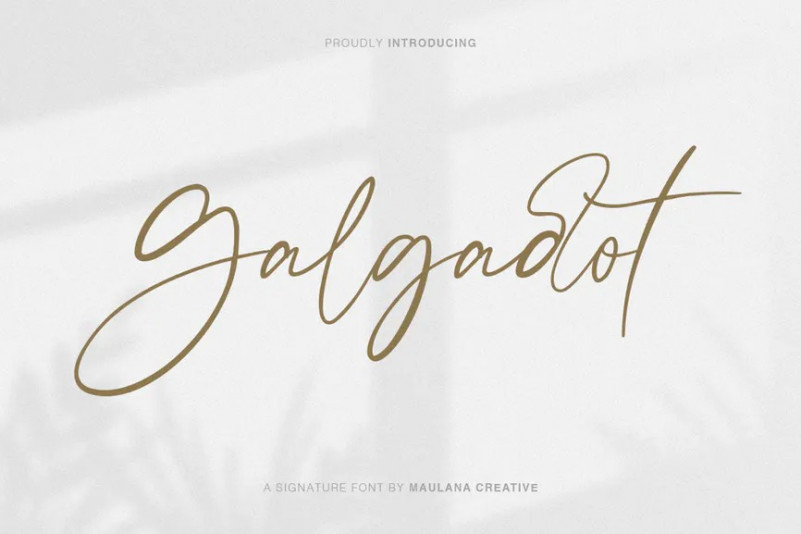
Galgadot Font
Donnez à vos créations une sensation artisanale authentique. « Galgadot » convient parfaitement à la signature, à la papeterie, au Logo, aux citations typographiques, à la couverture de magazines ou de livres, à l’en-tête de site Web, aux vêtements, à l’image de marque, à la conception d’emballages et plus encore.